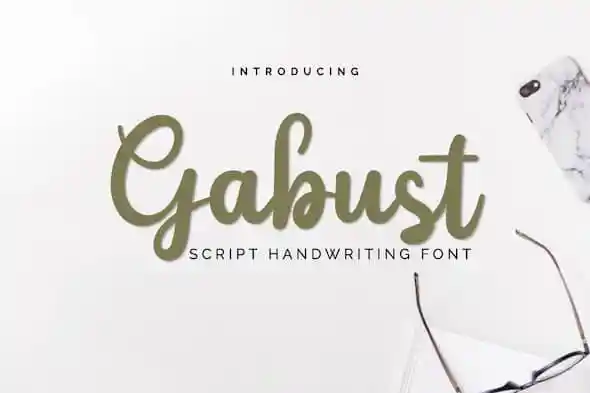
A Gabust Script Font é uma elegante caligrafia feminina que captura o encanto do estilo artesanal e suave. Seu charme delicado torna-a perfeita para ambientes pessoais, desde anúncios casuais até ilustrações de arte digital, sem perder a beleza e sofisticação necessárias para uso em uma variedade de projetos digitais. Além disso, é muito versátil e adaptável para criações que exigem um toque de autenticidade ou personalização única através da escrita à mão. Designada pelo designer twinletter, a Gabust Script Font se destaca como uma opção ideal tanto para aqueles buscando um estilo romântico quanto para quem deseja incorporar um pouco de personalização na sua arte digital.